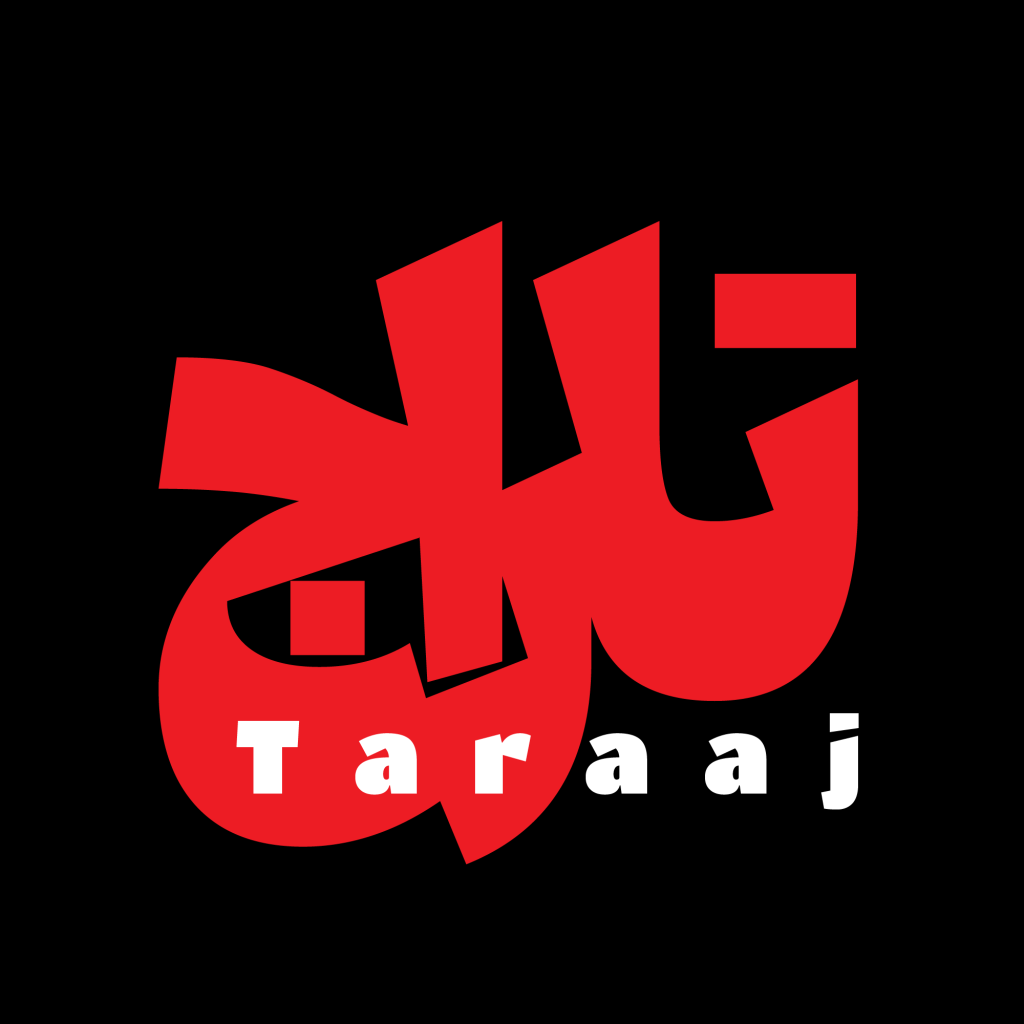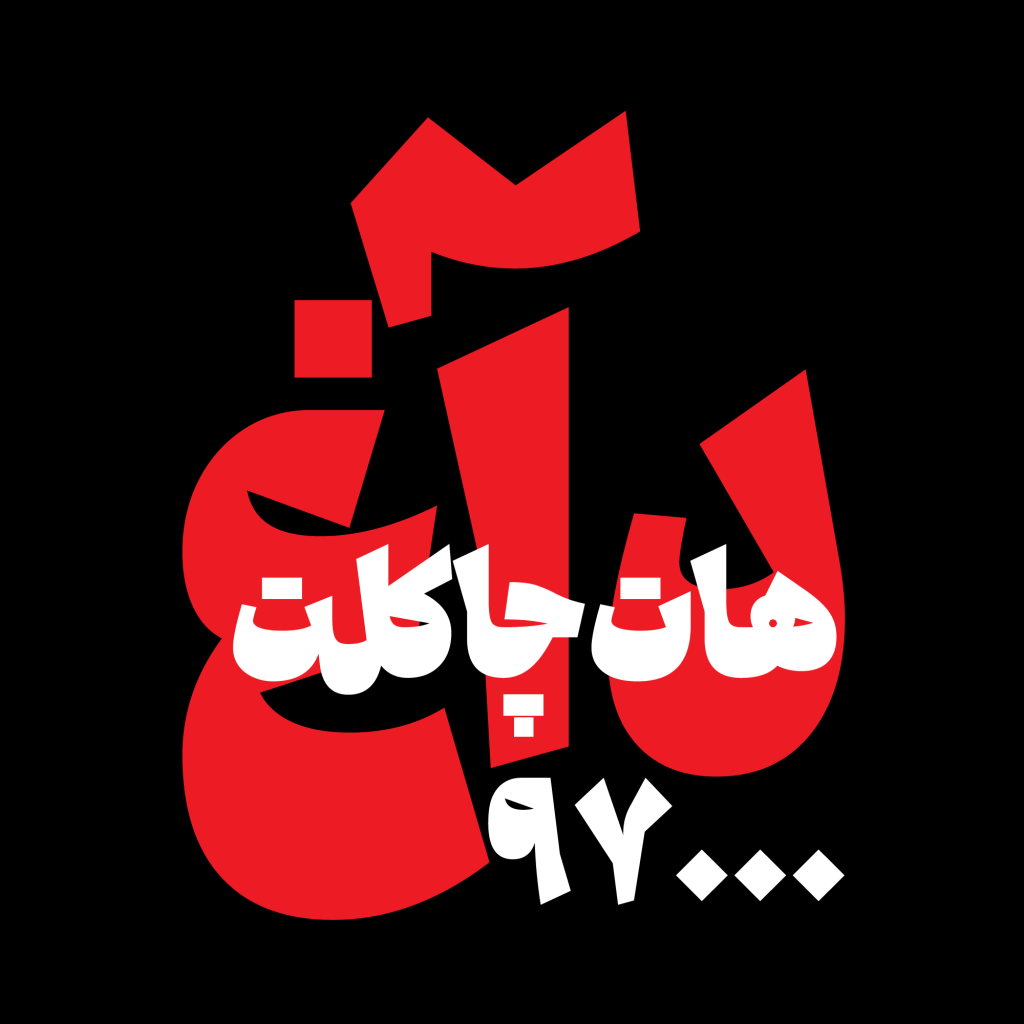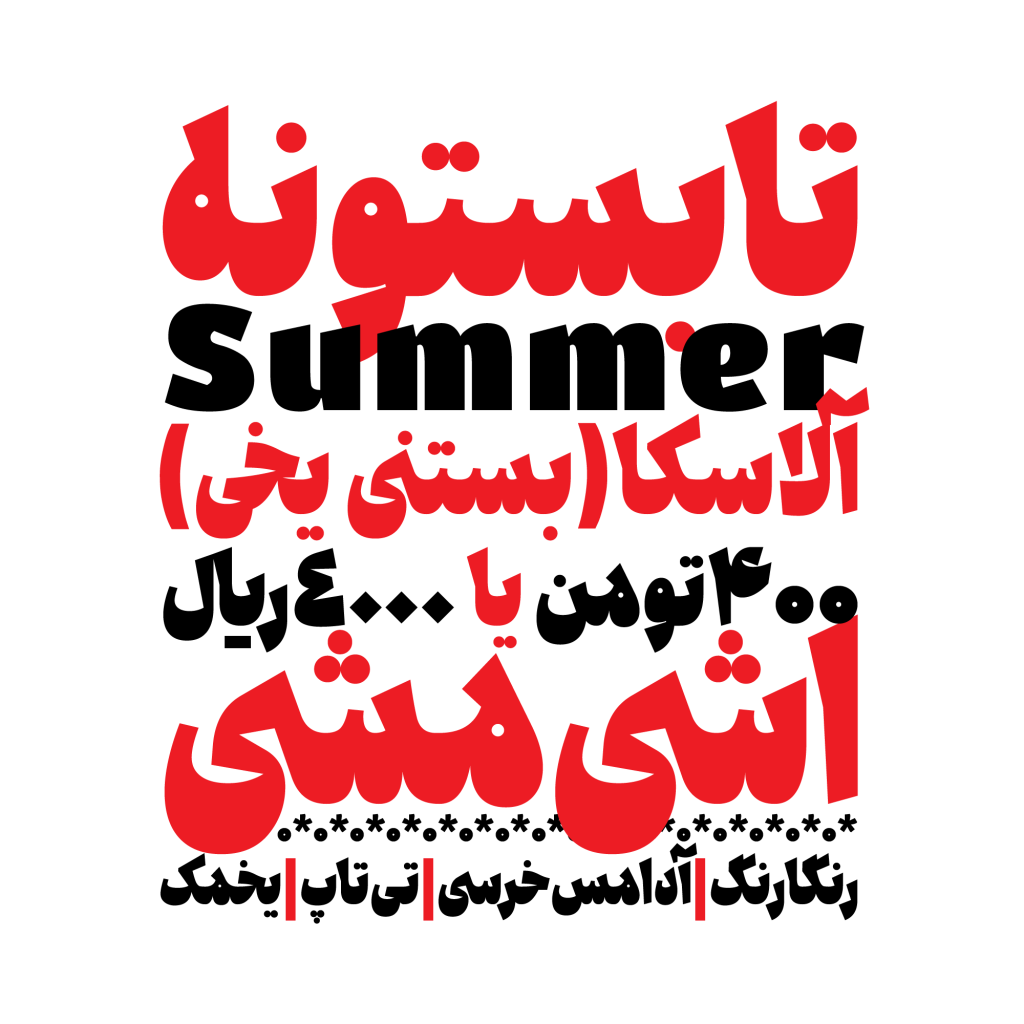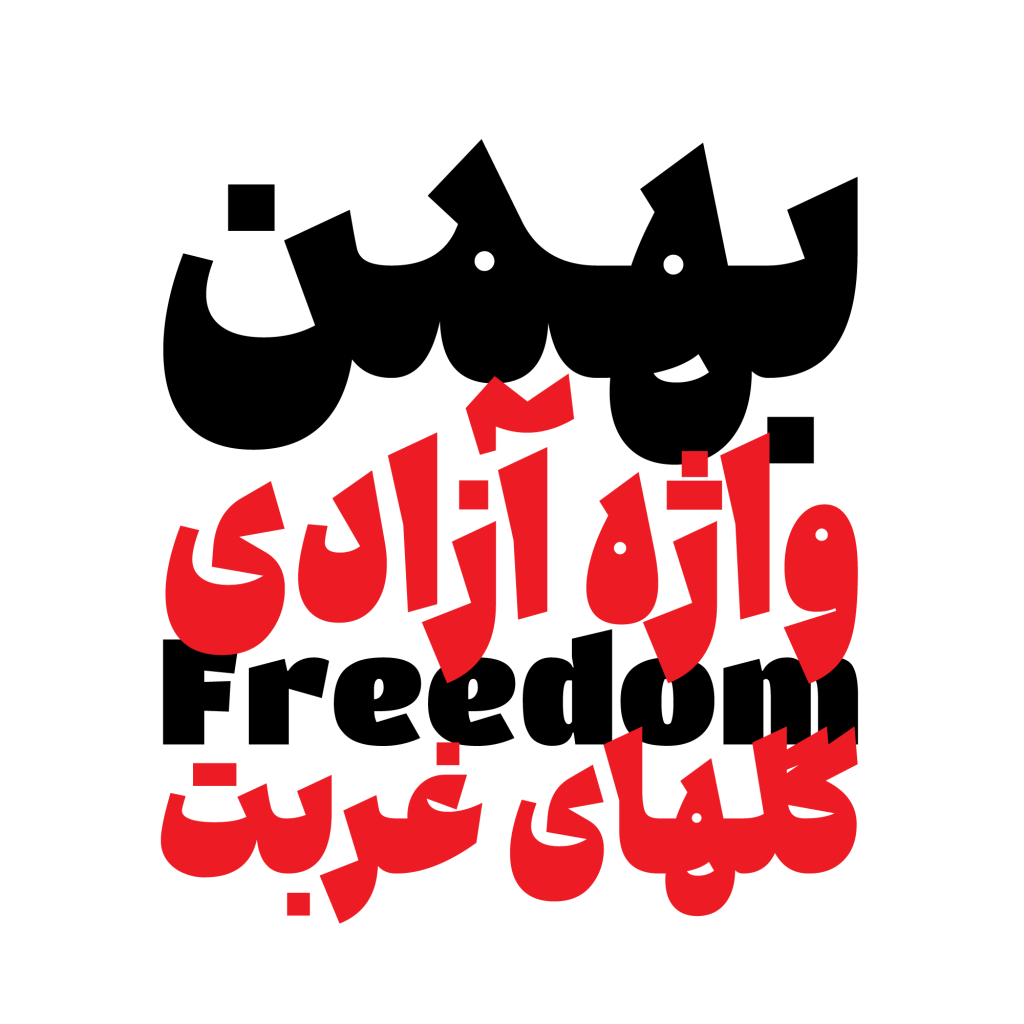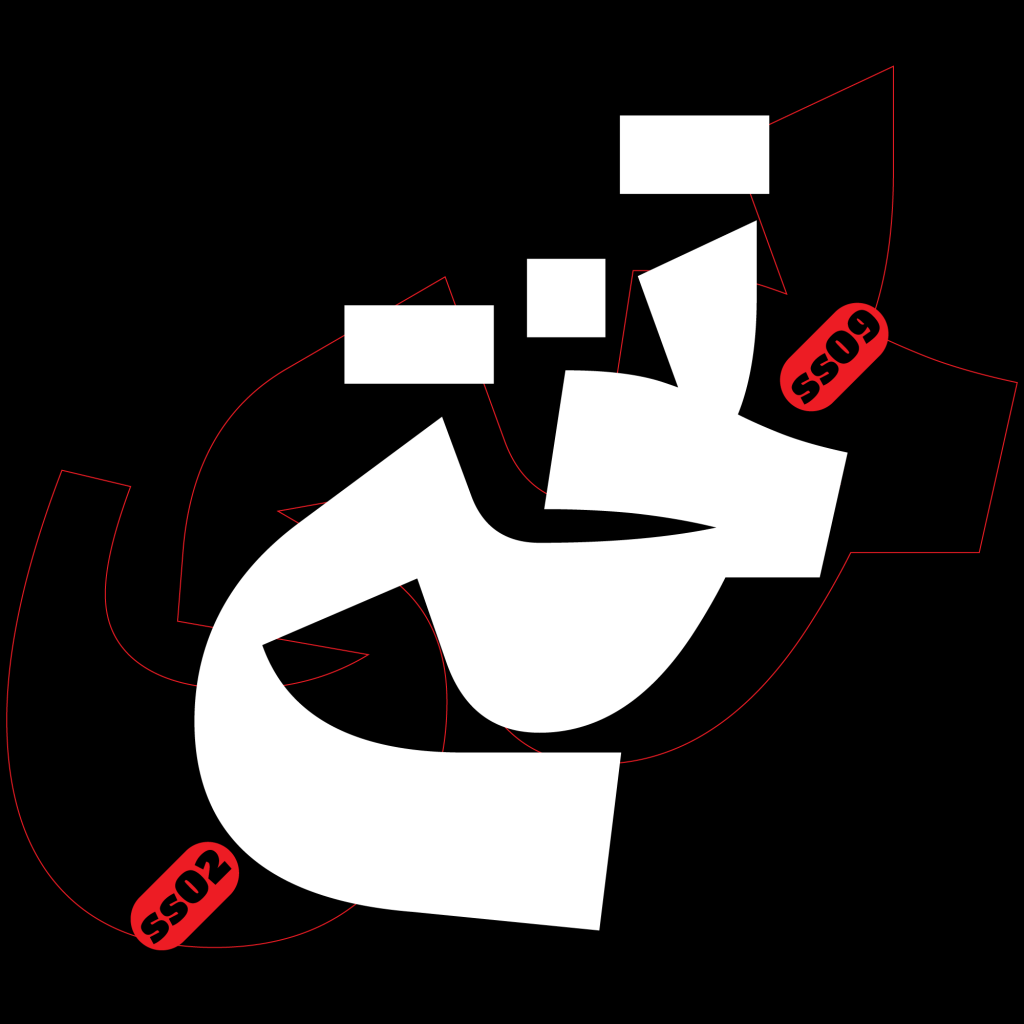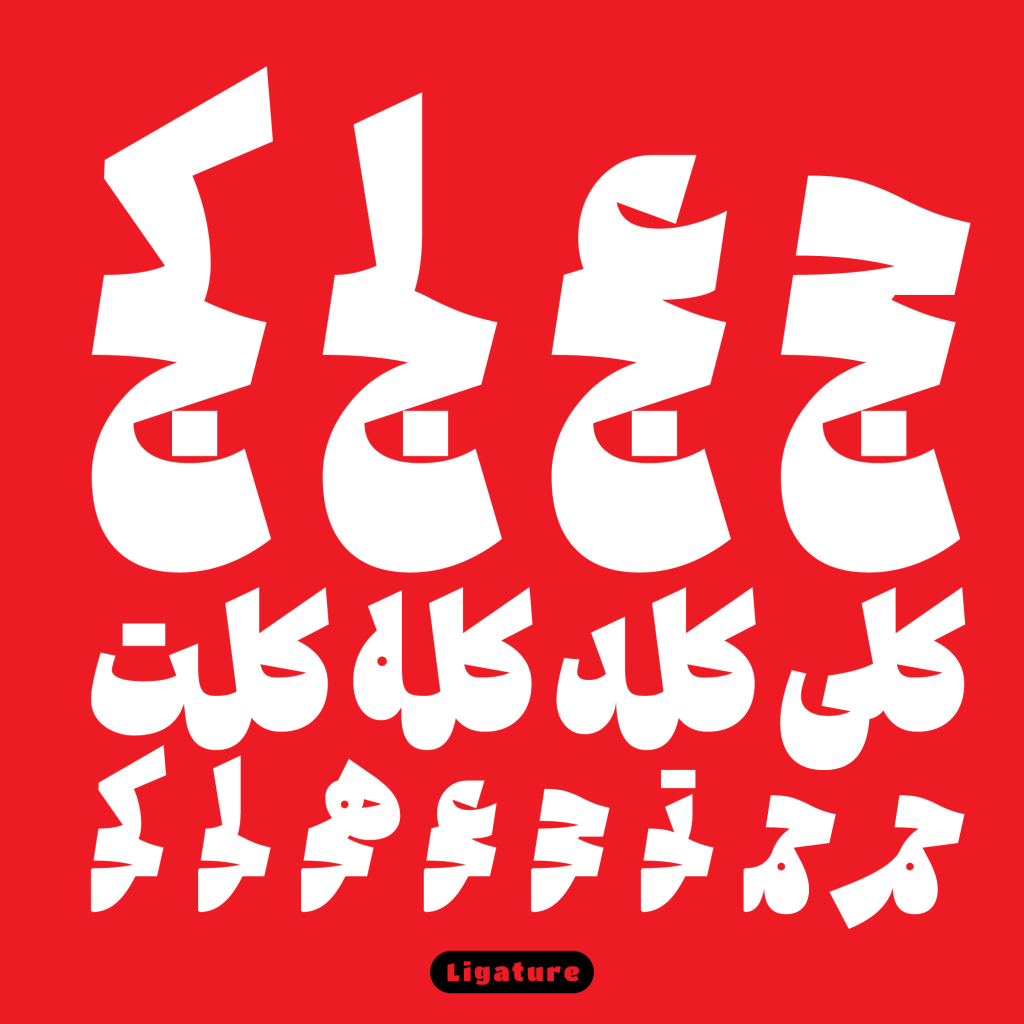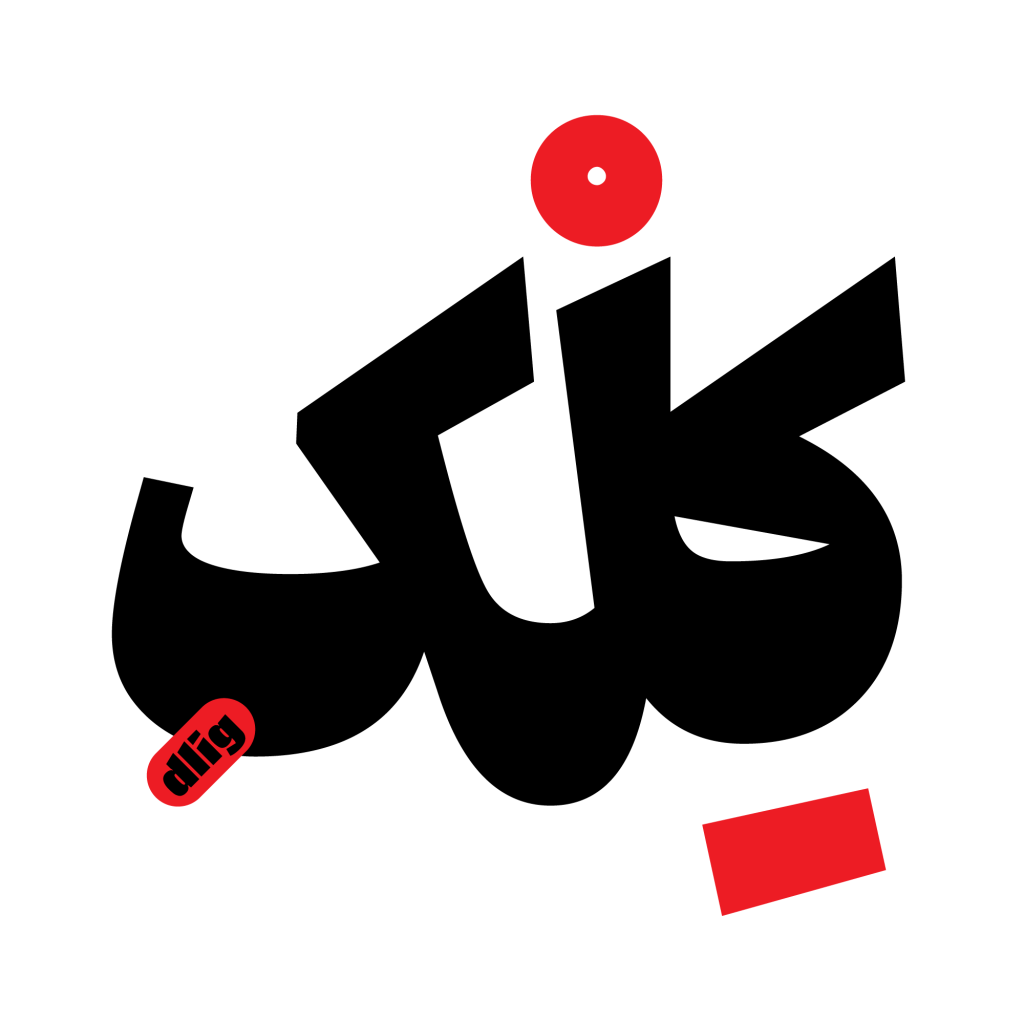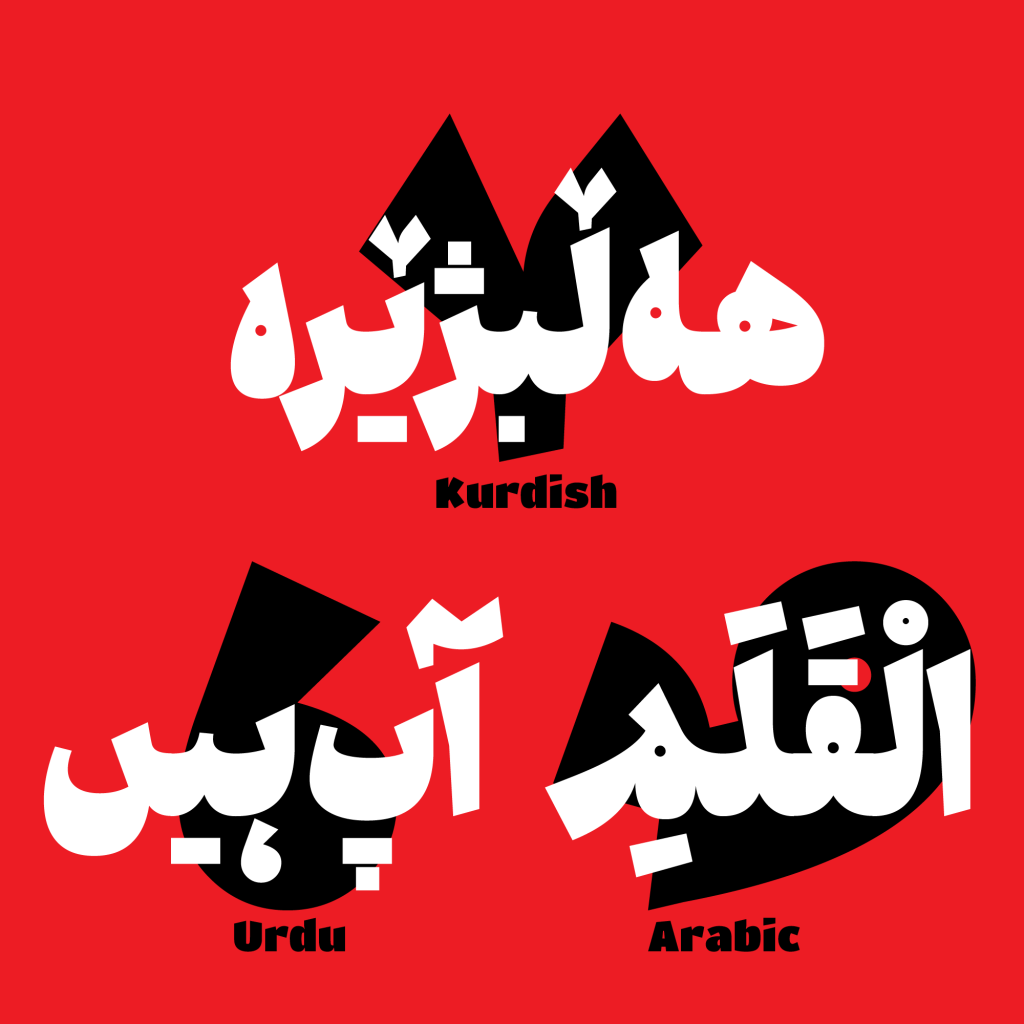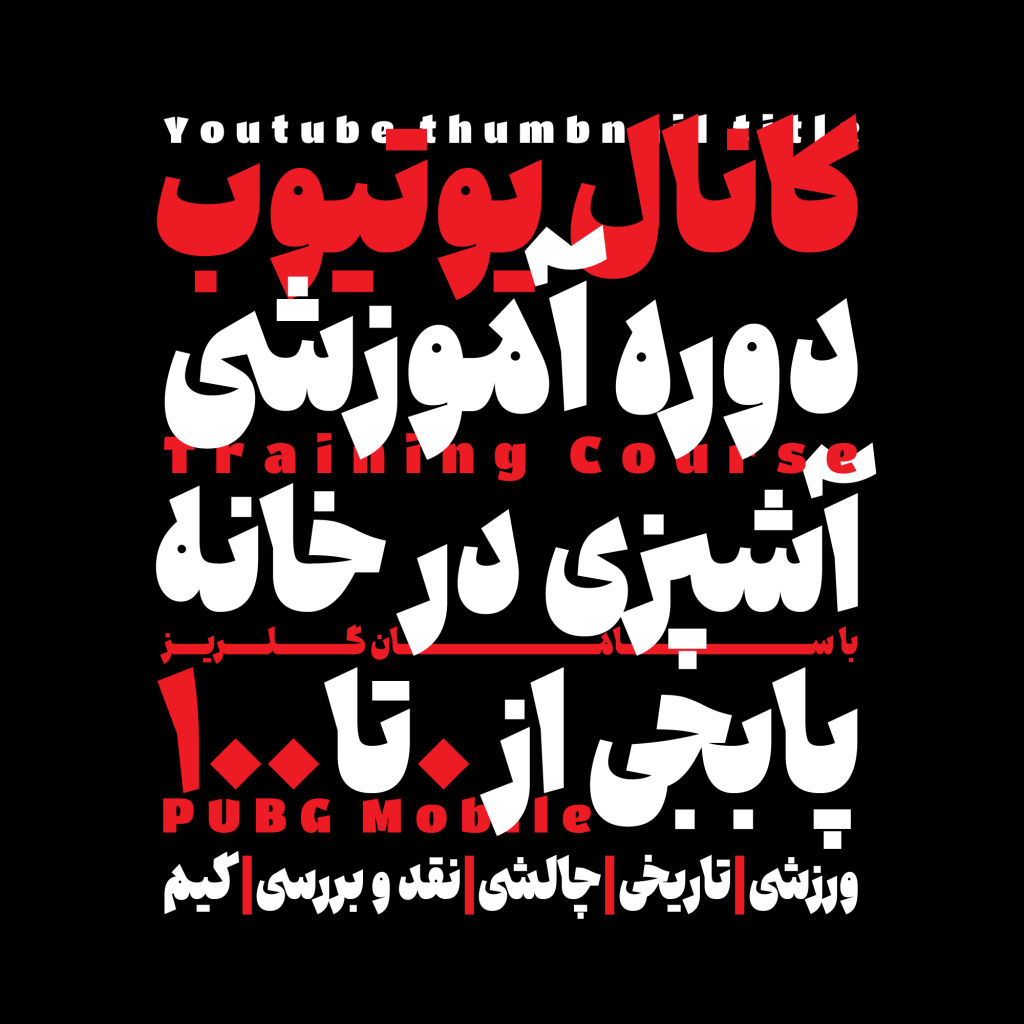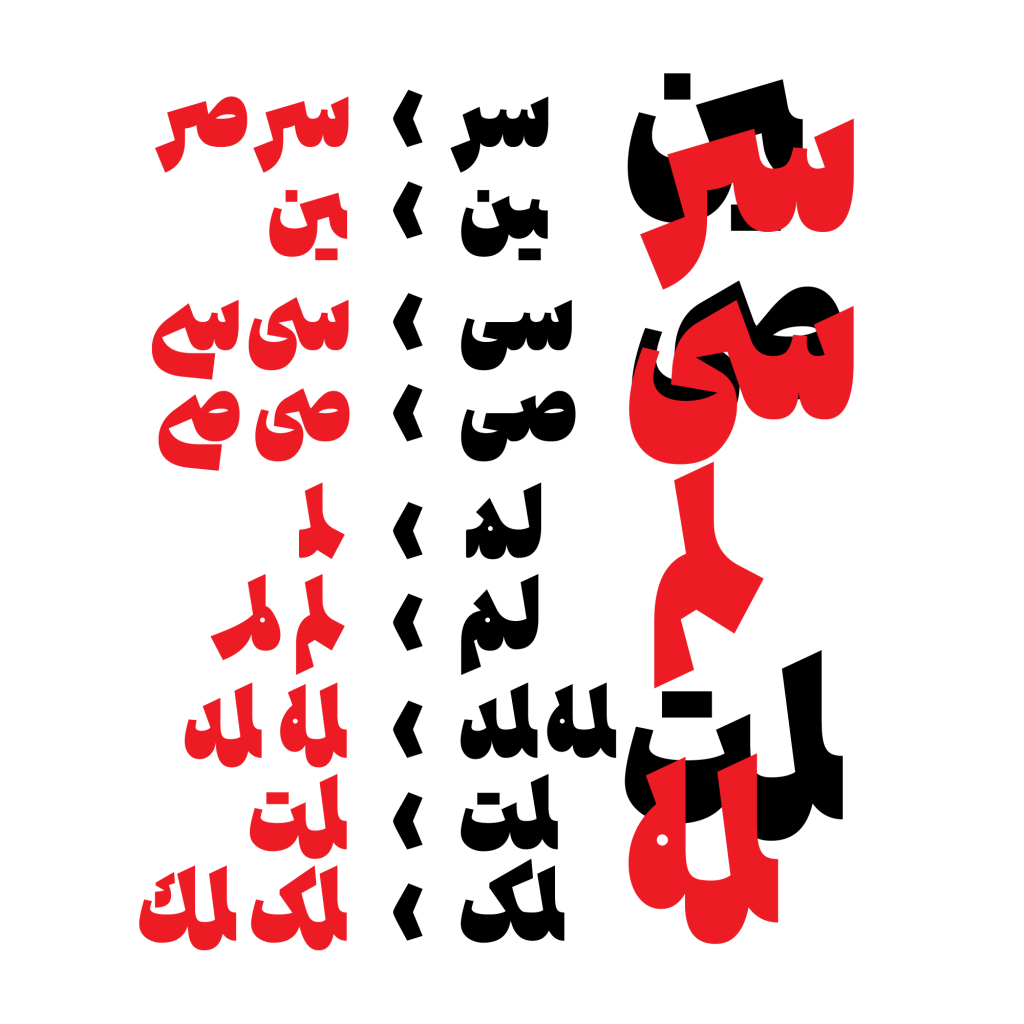
فونت جمله – قلمی با ویژگی نمایشی زیاد
فونت جمله قلمی که ویژگی اغراق و بزرگ نمایی جزء اصلی آن است فرم های ساختاری آن عمدتا از منحنی ها و خطوط با زوایای تند و تیز تشکیل شده است. از همین رو دارای کنتراست نسبتا بالایی در سطح می باشد.
این قلم به واسطه ویژگی هایی گفته شده مناسب برای متون کوتاه و عناوین و تیتر های با موضوعات مختلف است. چرا که هدف اصلی آن از خلق و ساخته شدن، دیده شدن و جذب نگاه مخاطبین بوده است.
این فونت حال و هوای تایپ فیس های دهه 50 رو داره اگه کمی توی فرم های ساختاری این قلم دقت کرده باشین مطمئنا متوجه تغییرات بنیادین و جسورانه شدین. دیگه خبری از تعادل و خونسردی نیست و همه تلاش تک تک اجزای تشکیل دهنده این تایپ فیس یک چیزه، دیده شدن.
جمله دارای 1 وزن و 2 سبک نقطه گذاری است.
داستان فونت جمله
از ایده تا اجرا ایده این تایپفیس در کلاس طراحی تایپ استاد ناصر خادم (زمستان ۱۴۰۳) مطرح و زیر نظر ایشان کامل شد. اولین حرف «ـه» بود که فرم آن به دو بخش تیز و منحنی تقسیم و همین ایده برای تمام حروف اجرا شد. در طراحی آن تلاش کردم که حروف تا حد ممکن متفاوت طراحی شوند تا یک فونت تیتر جذاب نیمه فانتزی و در عین حال خوانا داشته باشیم. استفاده در پوستر فیلم و نمایش، تیتر مطالب تبلیغاتی و تولید محتوای فضای مجازی از کاربردهای آن است.
حروف جایگزین و پشتیبانی از زبان های مختلف
حروف و ترکیبات دو و سه حرفی جایگزین متعددی در فونت جمله وجود دارد که با استفاده از راهنمای فونت میتوان از آنها استفاده کرد. در آپدیت آینده نیز ترکیبات بیشتر به آن اضافه خواهد شد.
فونت جمله برای زبان فارسی و عربی طراحی شده است و زبانهای اردو، کردی و انگلیسی را نیز پشتیبانی میکند. برای فونت انگلیسی آن از فونت اوپن سورس TitanOne استفاده شده است.